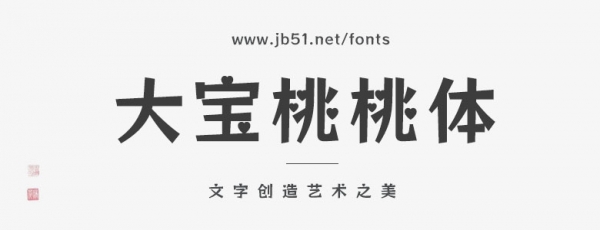
大寶桃桃體是貓啃網(wǎng)為大寶知識(shí)星球制作的一款字體,把圓點(diǎn)部件換成愛心,整體顯得可愛。十分適用于兒童,母嬰產(chǎn)品以及萌系動(dòng)畫等場(chǎng)合,為此類場(chǎng)景增添天真可愛,無拘無束,自由自在的活力。這款字體除了用作標(biāo)題,用于正文字體也有一種萌萌的感覺。